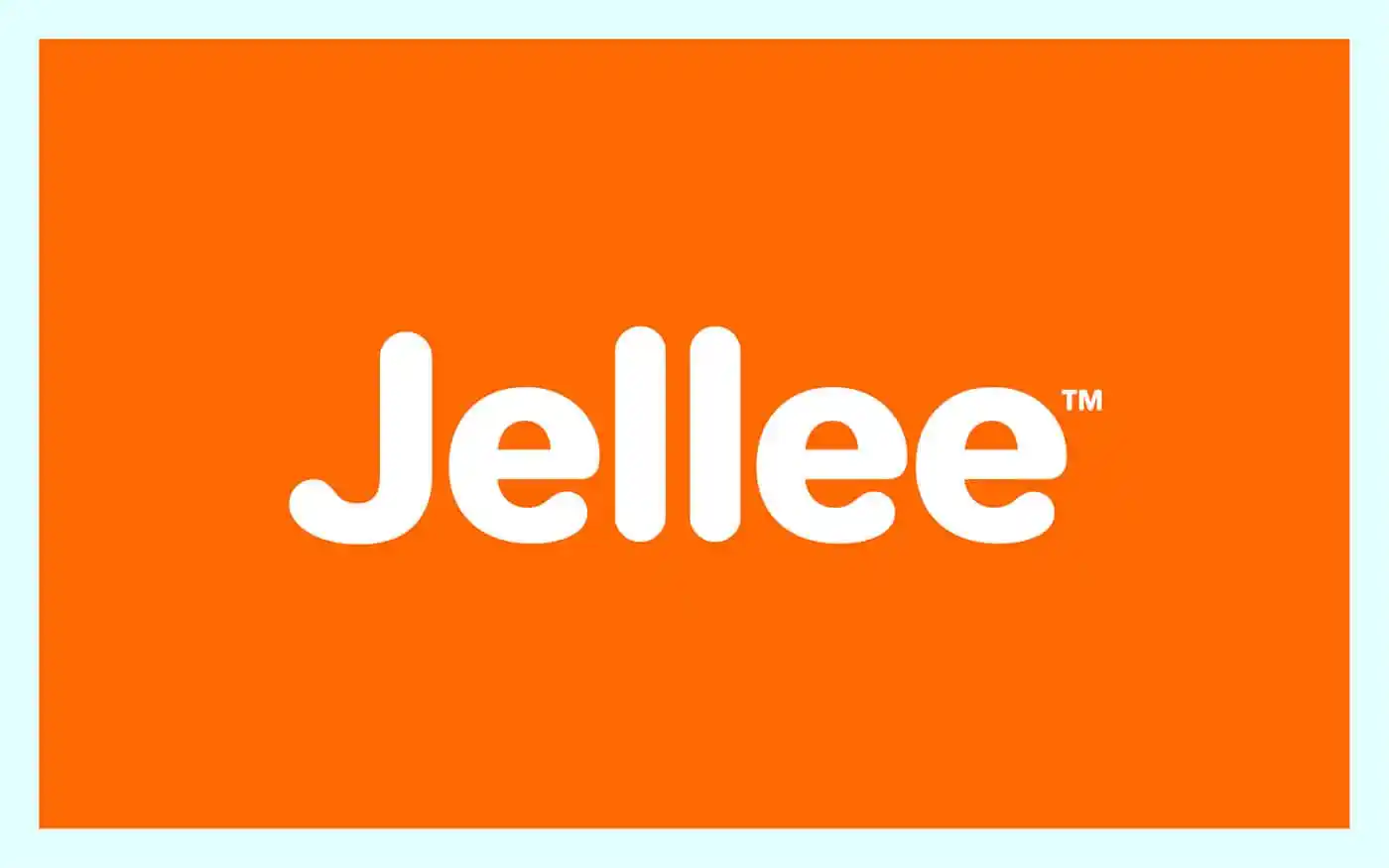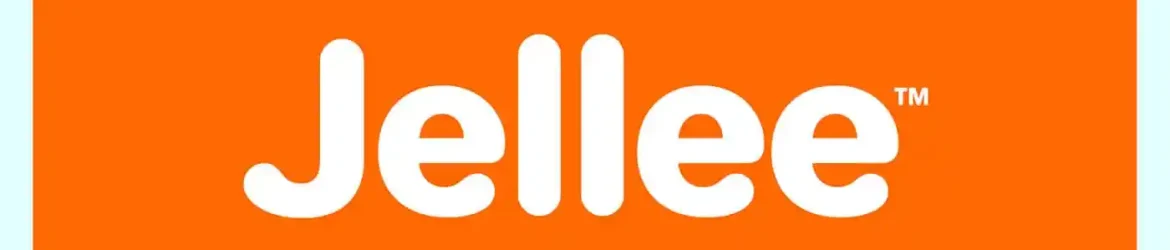
Jellee Typeface é uma fonte sem serif que traz um toque suave e amigável ao design de texto. Este tipo abraçado foi projetado para uso nos posters, headlines e títulos, dando uma aparência fresca e descontraída. A sua textura suave faz deste um recurso perfeito para animações de alta qualidade. Ideal para ambientes criativos e inspiradores, Jellee Typeface é uma escolha ótima para quem busca personalidade em seus projetos gráficos modernos e contemporâneos. É a escolha ideal para criações de animação que desejam um equilíbrio entre simplicidade e profundidade visual. Não importa se você está criando uma identidade visual, desenvolvendo um site ou mesmo produzindo conteúdo digital, Jellee Typeface traz sua personalidade única à vida em cada projeto.